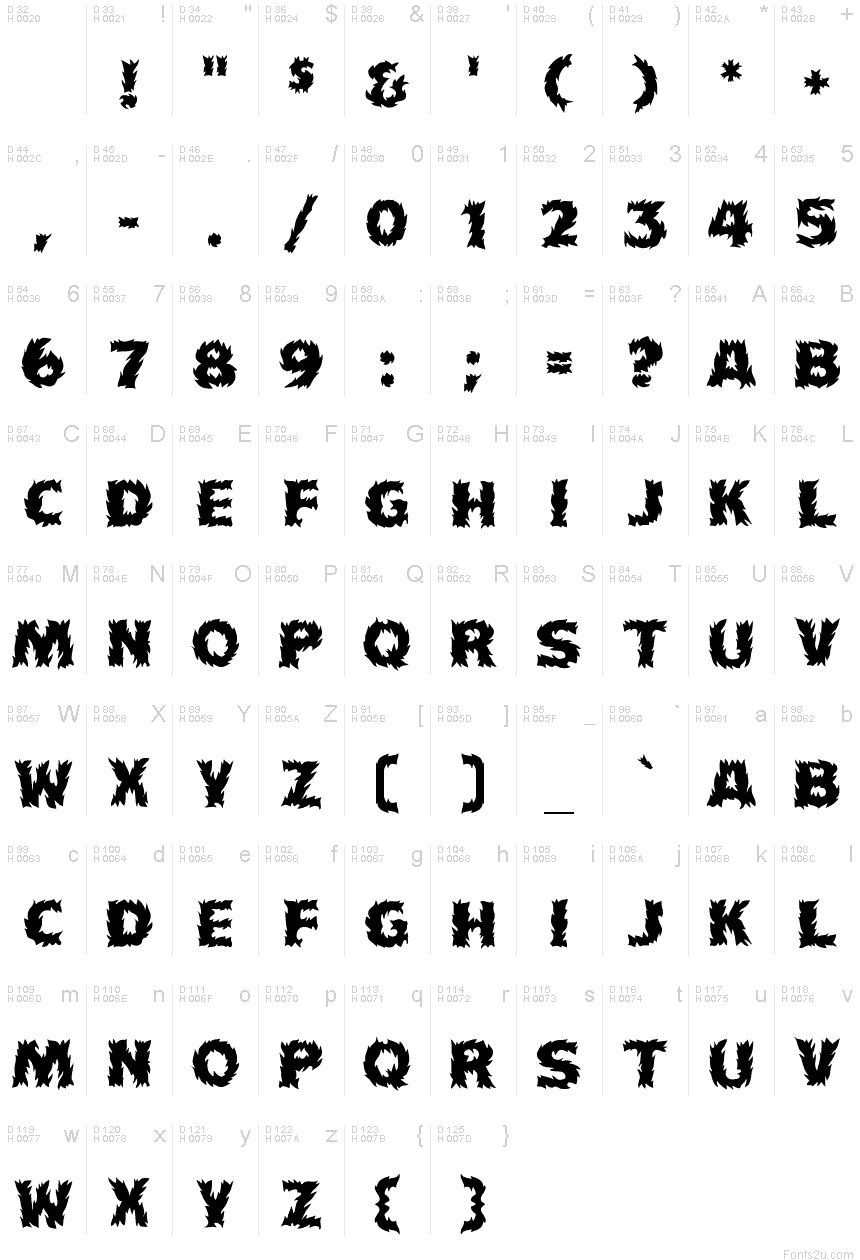
Flames autorstwa Richarda Williama Muellera to darmowy, zniekształcony krój pisma typu display, który wygląda, jakby został wycięty z litego, czarnego ognia. Każda litera najeżona jest poszarpanymi, migoczącymi krawędziami, sprawiając wrażenie, jakby kształty były smagane płomieniami i gnane gorącym wiatrem. Szorstka, przypalona faktura nadaje nagłówkom dziką, wybuchową energię, obok której nie da się przejść obojętnie.
Dzięki Flames podkręcisz swoje projekty – od horrorowych plakatów, logo zespołów metalowych i ulotek na Halloween, po tytuły gier, szyldy domów strachów czy wyraziste miniatury na YouTube. Ten darmowy font najlepiej sprawdza się w dużych rozmiarach, gdzie jego nieregularna sylwetka dosłownie wypala się w tło. Połącz go z prostym, neutralnym krojem bezszeryfowym w tekście uzupełniającym, aby całe gorąco pozostało w nagłówku.